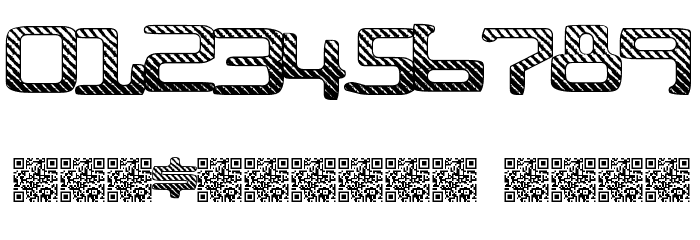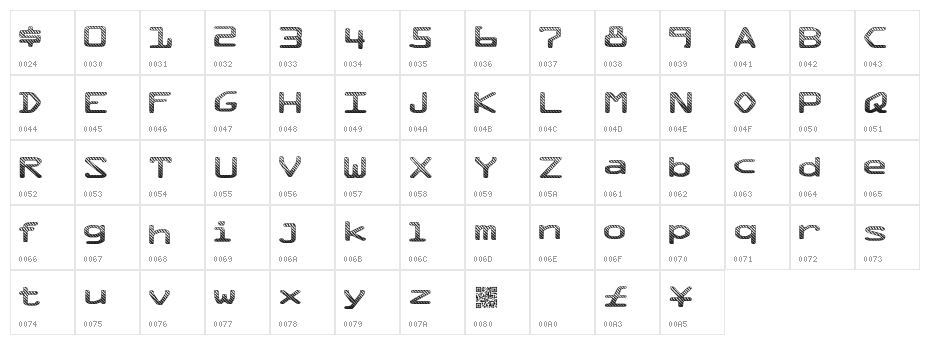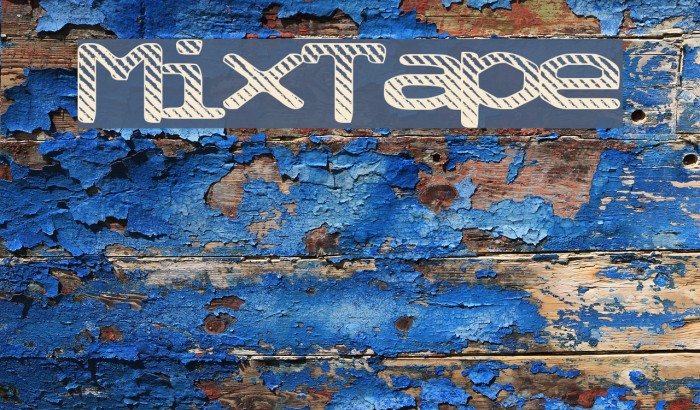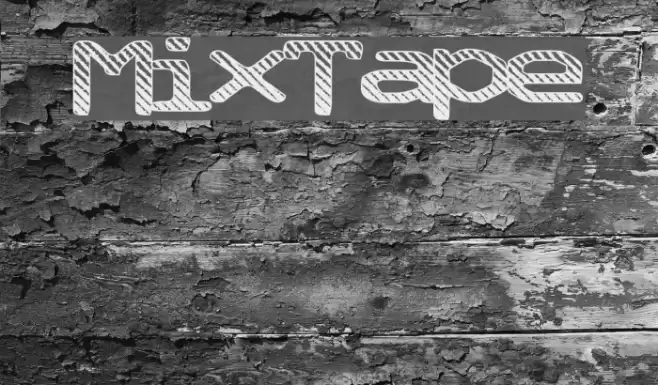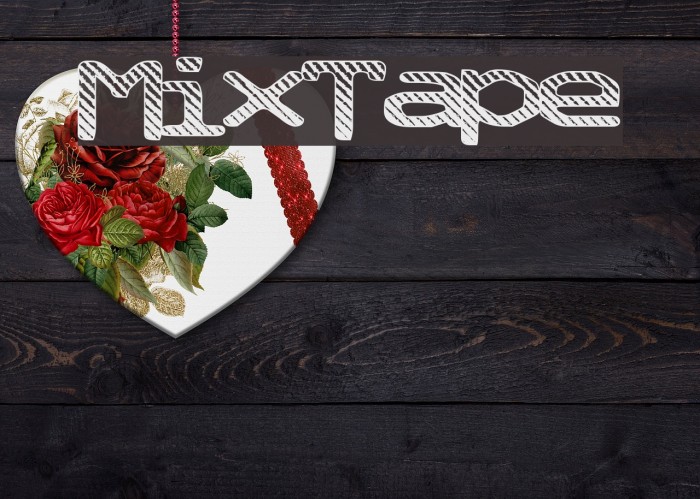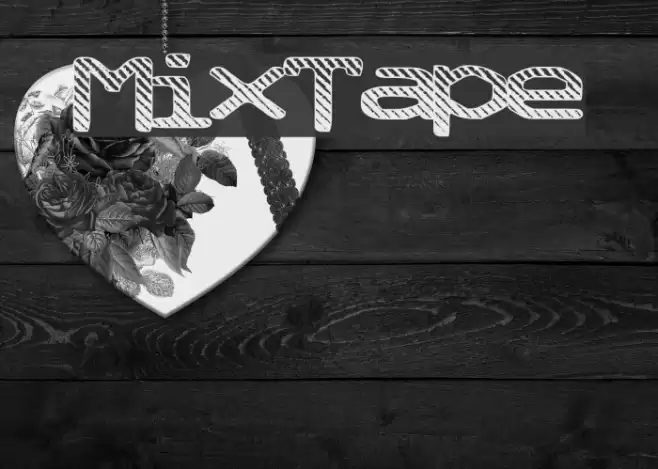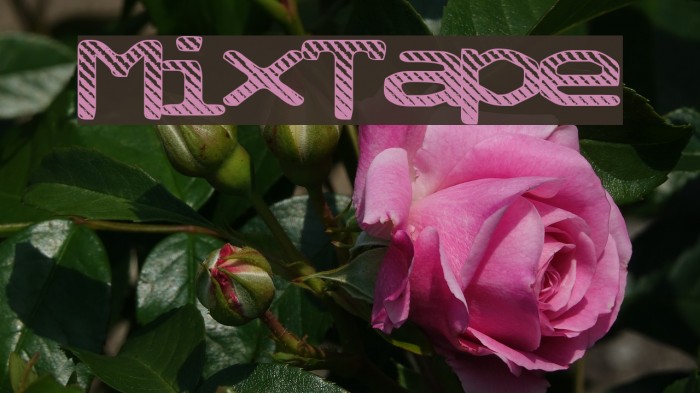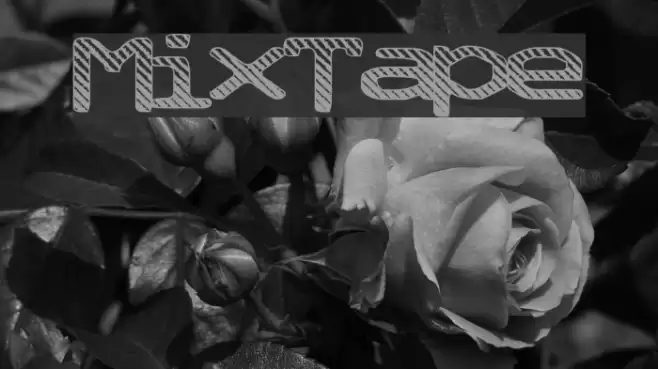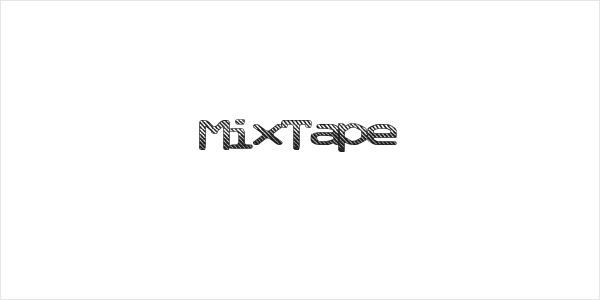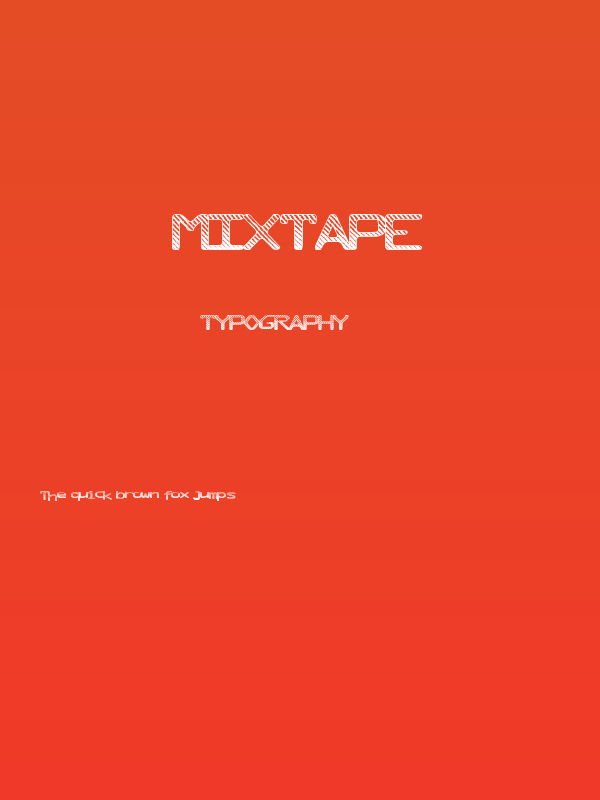
MixTape Font
| مشاريع مقترحة | Ideal for music-related projects, event posters, album covers, or any creative design requiring a modern and edgy look. |